편집자치곤 이상한 이야기.2_역할분담
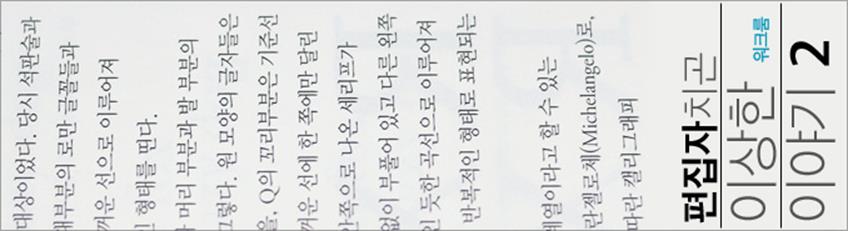
글. 박활성(워크룸프레스 편집장)
텍스트의 세계는 냉정하다. 무슨 말이냐 하면 ‘가’라고 쓰인 것은 다른 글자가 아닌 ‘가’라고 읽힌다는 뜻이다. 다른 여지는 없다. 무슨 뚱딴지같은 소리냐고 한다면 할 말이 없다. 당연한 말이니까. 학교에서 배웠듯 언어는 사회적 약속이다. 또 한편으로 텍스트의 세계는 한없이 열려 있는 가능성의 세계이기도 하다. 하나의 글자는 다른 글자들과 만나 무한한 의미를 생성해낸다. 편집자와 디자이너(타이포그래퍼)는 이 무한한 의미의 세계에서 일련의 글자들을 제자리에 놓고 거기에 알맞은 옷을 입히기 위해 고심하는 존재이다.
자, 지난 글에 이어 편집자와 디자이너의 애매모호한 역할 분담 내지는 갈등, 혹은 입장 차이에 대해 살펴보자. 편집자와 디자이너의 역할은 생각보다 많이 분리되어 있고, 그보다 더 많은 부분이 겹치기도 한다. 그나마 역할 분담을 해본다면 글자를 자리에 맞게 놓는 것은 편집자 쪽에 치우쳐 있고 옷을 입히는 것은 디자이너의 영역에 기울어 있을 텐데, 자리와 옷은 서로 영향을 주기 마련이라 자연히 문제들이 생긴다. 그 중 오늘 이야기해볼 것은 ‘줄바꿈’에 대한 이야기다.
앞서 이야기했듯 하나의 글자는 그 자체로는 별다른 의미를 생성해내지 못한다. 다른 글자와 결합해야 한다. 그런데 구텐베르크 이래 현재까지 적어도 종이책에서는 (그리고 현실적으로 엄연히 인터넷상에서도) 지면(혹은 화면)상의 한계로 줄바꿈이라는 게 필요하게 된다. 즉 어디서 텍스트를 끊고 줄을 바꿔주어야 할 것인가? 여기에 대해 생각해보지 않은 사람은 ‘그게 무슨 문제냐’고 반문할 수 있겠다. 그냥 종이가(화면이) 끝나는 데서 줄을 바꿔주면 되지. 하지만 현장에서 일하는 편집자나 디자이너 입장에서는 굉장히 현실적인 문제다.
물론 아주 오래 전에는 이게 문제가 아닐 수 있었다. 주어진 조건에 충실하면 되니까. 네모난 틀에 차가운 활자를 채워 넣어야 하던 시절에는 어디서 텍스트를 끊어야 하냐는 문제로 고민하는 건 호사에 가까운 일이었을 것이다. 하지만 기술적인 제약이 월등히 자유로워진 오늘날에도 줄바꿈의 문제는 가독성 문제와 더불어 정답이 없는 차가운 감자에 속한다.
더 구체적인 예를 들어보자. 우리 사무실만 해도 처음 일을 맡기는 클라이언트의 (적게 잡아서) 과반수 이상은 여전히 오른쪽 흘리기로 텍스트를 정렬했을 때 한 번씩 의문을 표한다. 특히 단행본 본문을 디자인할 때는 태클이 들어오는 게 정상이다. 처음에는 “이거 이렇게 정렬한 이유가 있나요?”라는 정도로 조심스레 시작하지만, 어떤 말을 늘어놓든 이내 “그냥 양쪽 정렬로 하면 안 될까요?”라는 말로 넘어가는 게 정해진 수순이다.
어디 차근차근 생각해보자. 먼저 텍스트의 정렬 방식을 결정하는 사람은 편집자일까, 디자이너일까? 원칙적으로 그것은 텍스트의 의미에는 심각한 영향을 주지 않는 시각적 형태, 즉 타이포그래피 영역에 속하므로 디자이너의 관할지에 좀 더 가깝다고 여겨진다. 하지만 그것은 원칙일 뿐이고, 줄바꿈은 엄연히 텍스트의 의미에 영향을 주기 때문에 편집자가 가만있을 수는 없다. 또한 여타 타이포그래피 영역 중에서도 본문 타이포그래피는 전통적으로 편집자의 입김이 많이 작용하는 편이라서, 솔직히 디자이너가 오른쪽 흘리기에 확고한 믿음이 없는 이상 편집자의 의견이 반영되기 쉽다. 세상에 꼭 오른쪽 흘리기로 조판되어야 하는 단행본 본문이란 찾기 힘든 것이다.
그렇다면 오른쪽 흘리기를 선호하는 디자이너들은 왜 오른쪽 흘리기를 선호할까? 사실 디자이너 입장에서는 꽤나 논리적인 나름의 이유를 댈 수 있다. 잘 알다시피 오른쪽 흘리기를 하면 훨씬 고른 자간을 유지할 수 있다. 양쪽 정렬처럼 글줄에 따라 보기 싫게 벌어지는 자간을 억지로 마이너스 자간을 먹여가며 무리하게 조절할 필요가 없는 것이다. 또 의미 단위별로 줄바꿈을 할 수 있으므로 단어나 조사 등이 쪼개져서 다음 줄로 넘어가는 일을 피할 수 있다. 텍스트들의 오른쪽 경계가 이루는 리듬감 있는 형태 역시 디자이너에게 매력적인 요소일 것이다.
일찍이 1920년대 피트 즈바르트(Piet Zwart)는 헤이그에 있는 트리오 인쇄소를 위한 안내서에 실린 「낡은 타이포그래피에서 새로운 타이포그래피로」라는 글에서 다음과 같이 말한 바 있다. “새로운 타이포그래피는 왼쪽 끝에 텍스트를 정렬시키고 끝나는 지점은 글줄의 길이에 맡기거나 혹은 일부러 줄을 바꿔 텍스트 내에 일종의 긴장감을 유도한다.” 이 밖에도 오른쪽 흘리기를 옹호하는 근거나 주장들은 멀리는 20세기 전반 새로운 타이포그래퍼들의 글부터 스위스 타이포그래피를 거쳐 오늘날에 이르기까지 어렵지 않게 찾아볼 수 있다. (하지만 오해하기 쉬운 사실로서 새로운 타이포그래피의 대명사 얀 치홀트(Jan Tschihold)는 ‘모더니스트’로 활동하던 동안 어떤 작업에서도, 심지어 광고에서도 일부러 이런 방식으로 활자를 조판하지 않았다. 그가 옹호한 것은 비대칭이지 오른쪽 흘리기가 아니다.)
그에 대한 반론들도 마찬가지다. 여기서 그 이야기들을 주구장창 늘어놓을 생각은 없고, 편집자치고 이상한 생각이 드는 것은 앞서 든 세 가지 근거 중 두 번째에 대한 것이다. 편집자들은 대개 텍스트의 의미 단위가 ‘디자인’이라는 행위에 의해 훼손되는 것을 별로 좋아하지 않는다. 그런데 양끝 정렬을 선호한다는 것은 왠지 앞뒤가 맞지 않는 것이다. 오른쪽 흘리기로 텍스트를 정렬하면 의미를 이루는 한 단위가 끊어지지 않고 온전히 붙어 있을 수 있는데, 왜 그걸 낯설어할까? 써놓고 보니 자문자답을 한 셈이다. 한마디로 낯설어서 그렇다.
요즘에는 그나마 오른쪽 흘리기로 된 책들이 간혹 눈에 띄지만 그래도 집에 있는 책을 아무 책이나 한번 펼쳐보면, 잡지나 시집 같은 걸 빼고 아마 99퍼센트의 단행본은 양쪽 정렬로 되어 있을 것이다. 그런데 처음부터 우리가 양쪽 정렬에 익숙해진 것은 아니다. 5~6세까지의 아이들을 대상으로 한 책들을 살펴보면 반대로 거의 90퍼센트 이상의 책들이 오른쪽 흘리기, 혹은 왼쪽 흘리기나 가운데 정렬로 되어 있지 양쪽 정렬로 되어 있는 책은 찾아보기 힘들다. 이유는 간단하다. 판형이 크고 문장들이 짧아서 줄바꿈을 할 필요가 없는 것이다. 결과적으로 자연스럽게 오른쪽 흘리기가 되니 가끔 등장하는 긴 문장들도 그에 맞춰서 정렬하면 된다. 그런데 초등학교에 들어가면서 상황은 정반대가 된다. 거의 모든 책들이 양쪽 정렬로 조판되고 결과적으로 우리는 양끝 정렬에 길들여진다. 이거 참.
그런데 낯선 게 편집자에게 왜 문제가 될까? 낯설다고 해서 그게 잘못된 것은 아니고, 더군다나 실제로 독자들은 양끝 정렬이든 오른쪽 흘리기든 잘도 읽을 텐데 말이다. 아마 모두 그렇진 않더라도 대부분의 독자들은 그럴 것이다. 처음에는 낯설더라도 내용을 따라가다 보면 그런 건 독서에 그다지 큰 영향을 주지 않는다. 우리 모두는 조악한 인터넷 타이포그래피 환경마저 잘도 견뎌내는 사람들이니까. 그렇다면 의미 단위가 끊어지지 않는 오른쪽 흘리기가 더 낫지 않을까? 그런데 솔직히 이런 말 하면 같은 사무실에 있는 디자이너들이 뭐라 할지 모르겠지만 나만 해도 단행본 편집을 할 때 양쪽 정렬을 선호한다. 그게 왠지 맘이 놓이고 교정을 보고 난 후에도 뒷맛이 개운하다.
왜 그럴까? 그게 아무래도 익숙해서 자연스럽게 느껴지기 때문이다. 실제로 그렇든 아니든 가독성이 더 좋다고 생각하기 때문이다. 따지고 보면 양끝 정렬이 텍스트에게 굉장히 폭력적이고 인위적인 방법임에도 불구하고 오히려 오른쪽 흘리기가 더 인위적으로 느껴지기 때문이다. 즉 디자인이 ‘개입’된 것 같기 때문이다. 디자인을 하겠다는 디자이너의 의지, 혹은 태도가 느껴진다고나 할까. 아무튼 그런 낌새가 낯선 느낌과 결합해 심리적 거부감을 들게 하는지도 모른다. 그리고 어쩌면 그건 편집자들의 텍스트에 대한 욕망이 반영된 결과일지도 모르겠다. 내가 지금 다루는 텍스트를 온전히 내 손 안에서 통제하고 싶은 욕망. 이상하게도 도록이니 리플렛이니 이런 것들은 다 괜찮은데 단행본일 경우에는 오른쪽 흘리기로 되어 있으면 내가 텍스트를 장악하고 있다는 느낌이 엷어지는 것이 사실이다. 덧붙이자면 그렇다고 텍스트에 대한 장악력이 온전히 디자이너에게 넘어가지도 않은 어정쩡한 느낌.
그리하여 나는 앞서 오른쪽 흘리기를 옹호하는 세 가지 이유를 똑같이 들어 양쪽 정렬을 주장하곤 한다. 즉 고른 자간을 유지하면서, 형식적인 단어별 줄바꿈 말고 진정한 의미의 의미 단위별 줄바꿈을 실현함과 동시에, 텍스트의 오른쪽 경계선이 이루는 시각적 리듬감 역시 아름다운 오른쪽 흘리기가 아닌 다음에야 양쪽 정렬이 더 좋다는 것이다. 제아무리 테크놀로지가 발달했다 하더라도 이 세 가지 조건을 모두 충족시키는 아름다운 한글 오른쪽 흘리기를 하려면 말 그대로 ‘엄청난’ 노가다가 필요하다. 똑똑한 척만 하는 컴퓨터 프로그램에 맡겨놔서는 오른쪽 흘리기의 장점을 운운하며 편집자를 설득하는 건 무리인 것이다.
그리고 솔직히 개인 작업이 아닌 다음에야 바쁘게 돌아가는 실무에서, 그것도 긴 텍스트에서 이걸 실현할 수 있는 편집 디자이너는 우리나라에서 다섯 명도 채 되지 않는다고 생각한다. 그런데 나 자신도 이해할 수 없는 건, 단행본에 있어서는 양쪽 정렬이 더 좋다고 실컷 말해놓고도 정작 워크룸 프레스에서 출간하는 책들은 거의 대부분 오른쪽 흘리기로 되어 있다는 사실이다. 이 표리부동을 어떻게 해명해야 할까? 어쩌면 그건 텍스트의 냉정함이 때로는 싫기 때문인지도 모른다. 어차피 편집은, 그리고 디자인은 텍스트를 통제할 수 없고 우리가 텍스트에게 남길 수 있는 것은 그저 흔적일 뿐이라는 사실을 알고 있기 때문인지도 모르겠다.